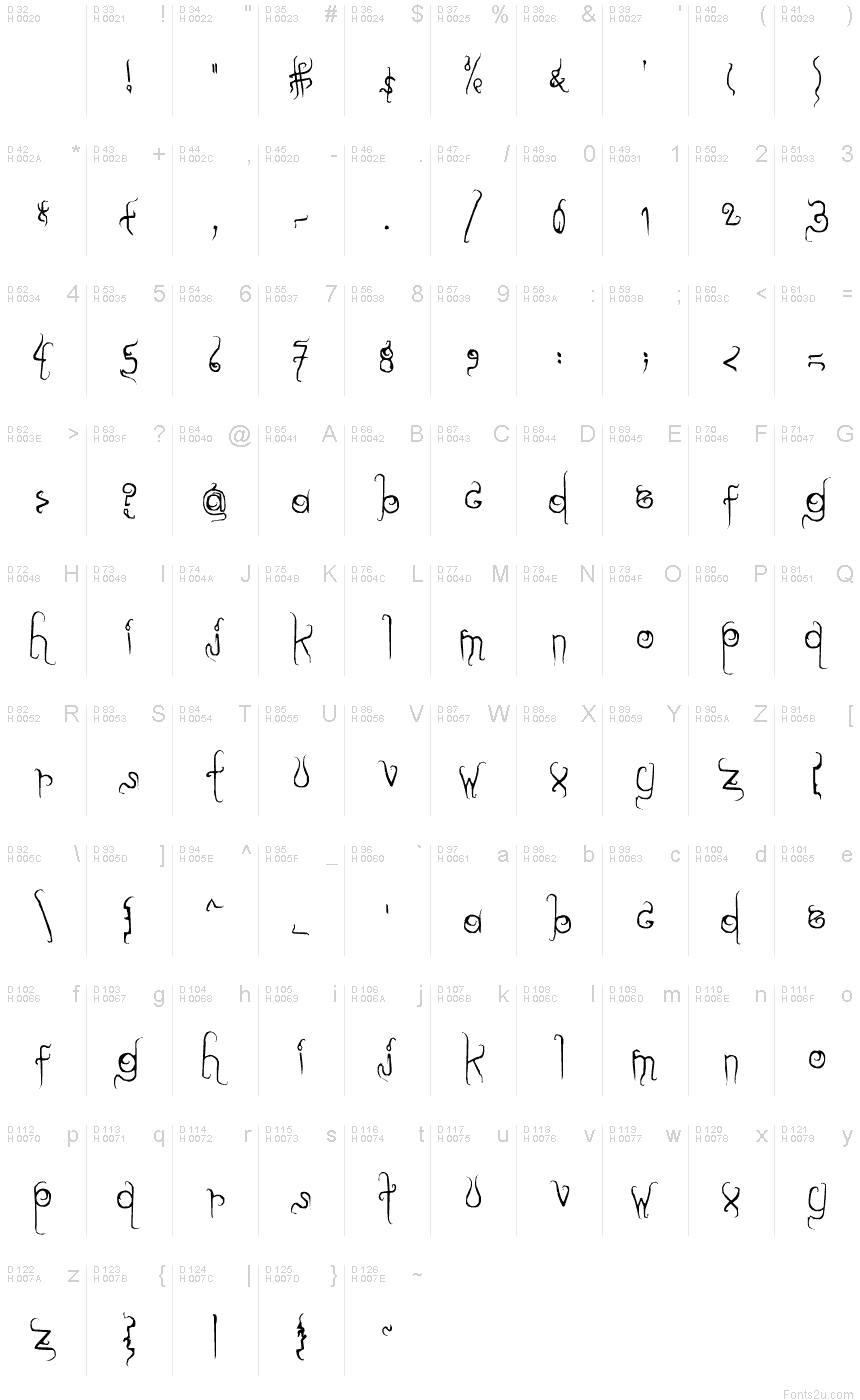
Dilate è un font display decorativo e gratuito che sembra schizzato con una penna a inchiostro graffiante. I suoi tratti alti e filiformi si arricciano in spirali strette, mentre le forme arrotondate si gonfiano e si restringono come rampicanti attorno a una recinzione. Il ritmo risulta un po' inquietante e fuori dagli schemi, conferendo a ogni parola un fascino mistico e disegnato a mano.
Con Dilate, puoi spingere i titoli di poster di band, copertine di album, libri dark fantasy, zine occulte, volantini di Halloween e brand di moda alternativa verso territori più strani e memorabili. Questo font gratuito dà il meglio di sé in grande formato, dove le sue curve aggrovigliate possono respirare; abbinalo a un sans serif geometrico pulito nel corpo del testo per mantenere la leggibilità e un impatto sorprendente.